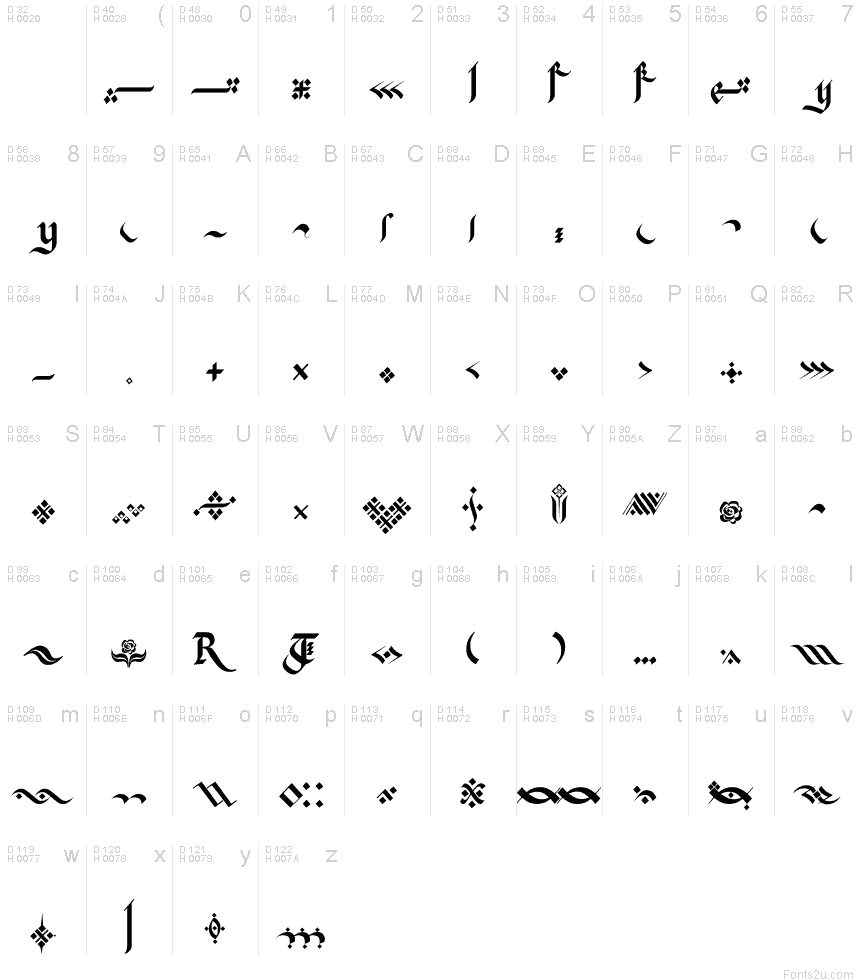
Kingthings Flourishes 字体
Kingthings Flourishes
Kingthings
Kevin King
Kingthings Flourishes 是一款来自 Kingthings Flourishes (Kingthings 2003) 的免费装饰性 dingbat 字体。它的符号结合了流畅的弯月弧线、尖锐的叶状形态、紧凑的菱形和十字形标记,配合强烈的黑色剪影与清晰的几何切口,让人联想起传统的印刷商花饰。
邀请函和证书可以将这些花饰用作分隔线、角部细节或小型徽章,特别是当设计需要带有略微个性特色的正式装饰时。它们也适合用于书籍封面和精品包装,其中的曲线部件可以成为边框,菱形图案则可以作为装饰纹样重复出现。